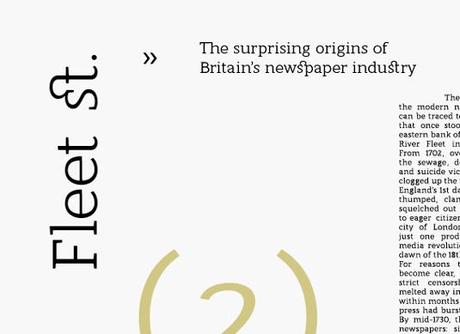
Visto che la rete é piena di free font da utilizzare per lo sviluppo del nostro design, oggi voglio condividere con te questo nuovo carattere, totalmente gratuito, che può essere di aiuto per un design unico, originale e al passo con i tempi. Eccoti Modum Font.
Modum Free Font
Un moderno e contemporaneo font sans serif creato e sviluppato dal team The Northern Block. Modum Font é un carattere elegante, armonioso e pratico adatto ad innumerevoli tipologie di progetti. Forme decise e angoli accuratamente disegnati che rendono questo carattere fresco e lo distinguono dai soliti web fonts.